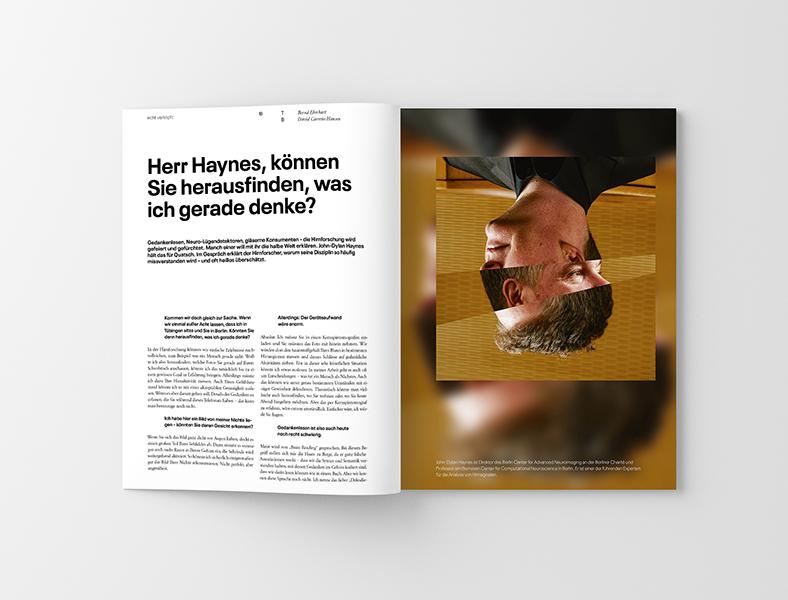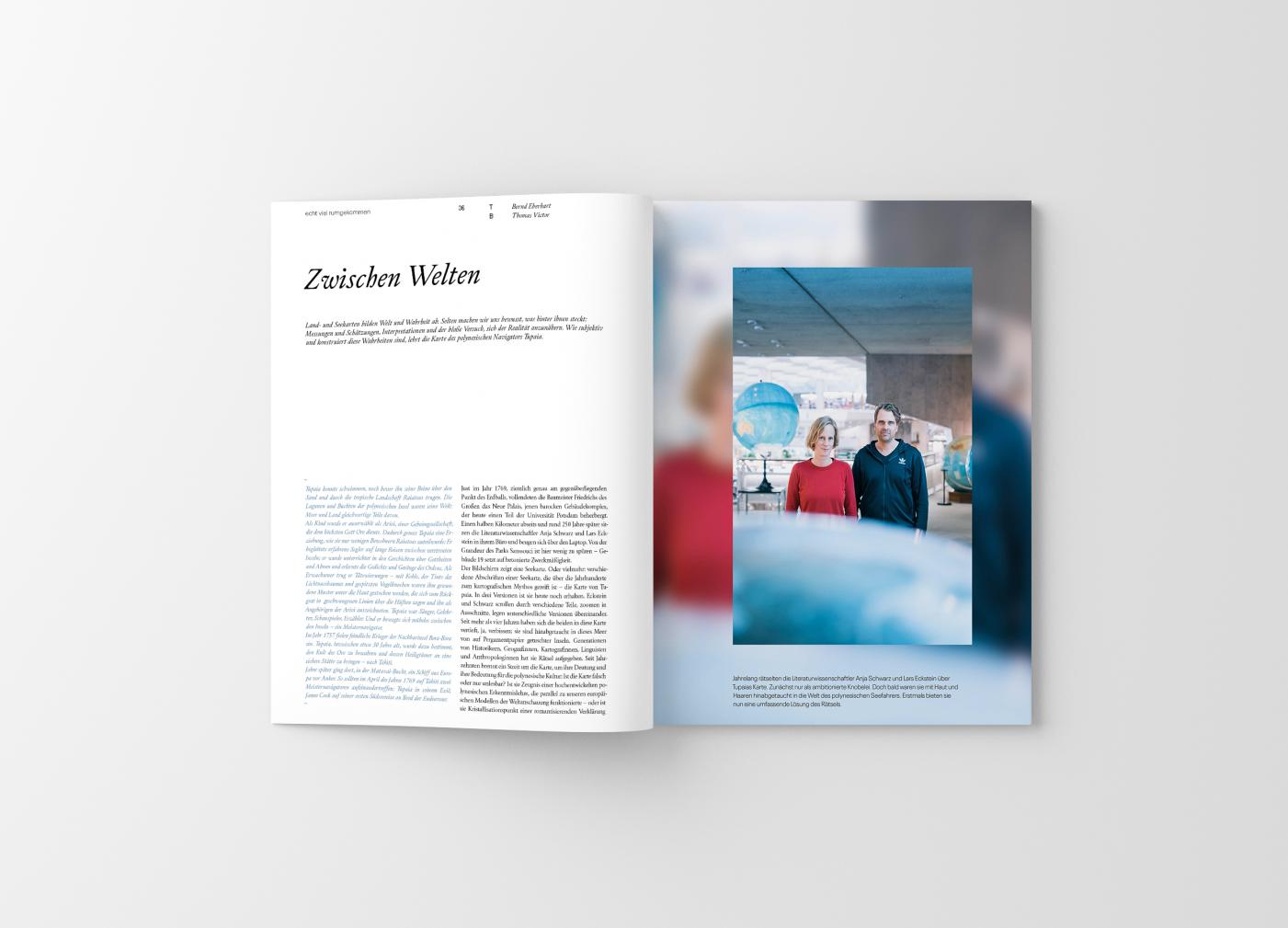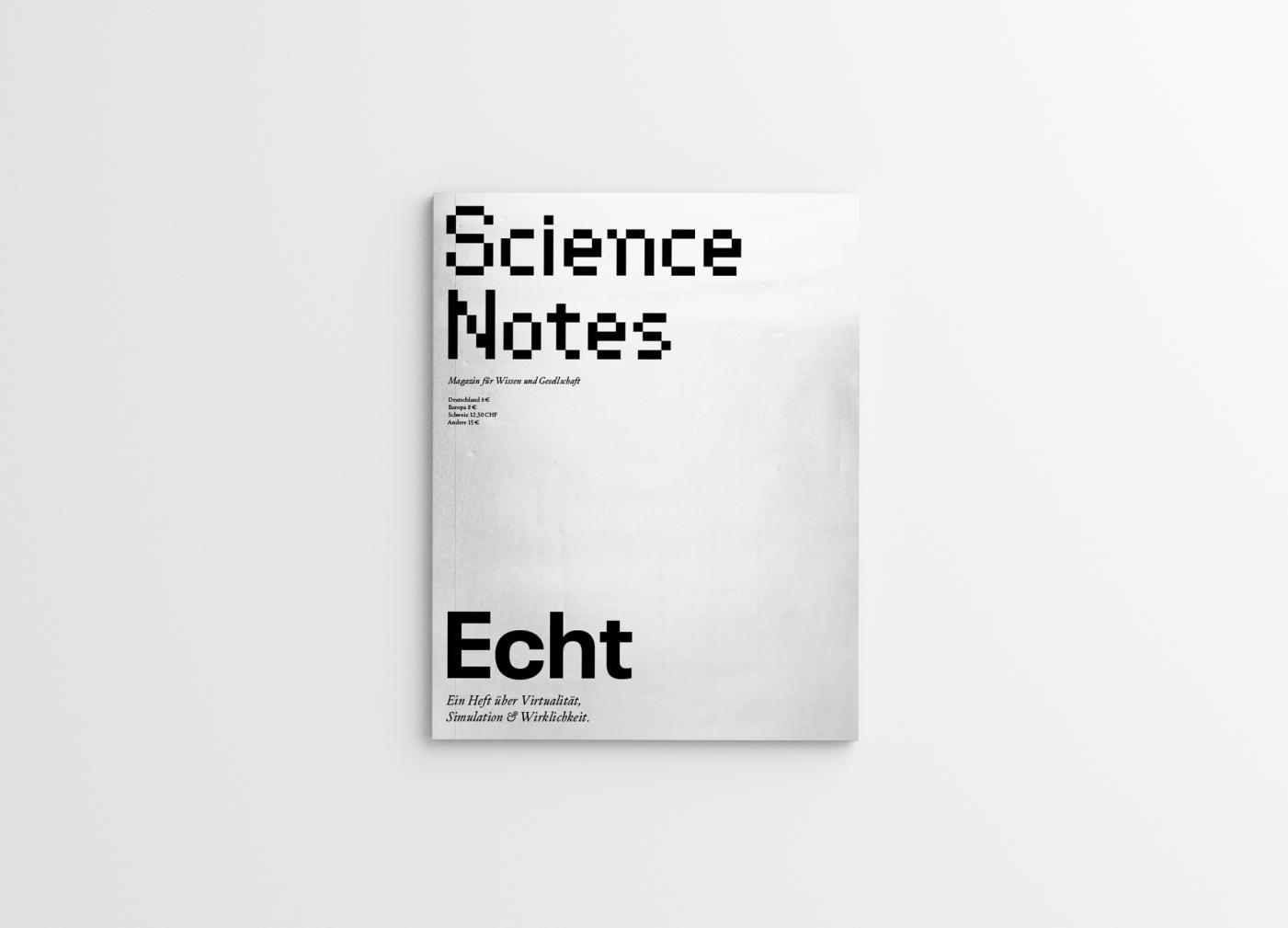
Welche Schriften verwendet das Magazin Science Notes ?
ich suche (Recherche) die Schriften (Headline, Titelblatt, Pagina, Fliesstext, etc.) die bei der dritten Ausgabe (2019)  des Magazin's "Science Notes verwendet werden.  https://snmag.de/kaufen/03-echt/
Was mir aufgefallen ist. Das kleine r der Kapitelüberschrift (Abb.3)
Hier ein Bild der Titelseite:
Abb.1
Noch eine Seite aus der Ausgabe.
Abb. 3
Das sieht sehr nach der Plak aus:
Also die Neue Plak hab ich mal angeschaut. Das kommt hin für die Headlines/Subheader. Cool! Witzig, dass das besondere  r (tropfenrund) erst beim Schnitt „black“ auftaucht.
https://playtype.com/sites/default/files/font_type_specimen/Primo-Serif_Playtype.pdf Auf Seite 7 sieht man hier schön das große W. Schön!
Erkennt jemand die Schrift in der Science Notes auf der Titelseite gesetzt ist?